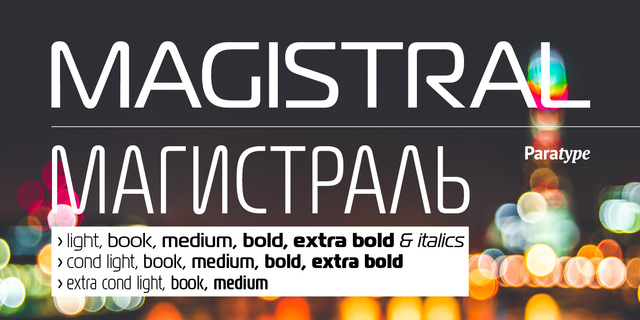
Первые три начертания гарнитуры были разработаны в фирме ПараТайп (ПараГраф) в 1997 году дизайнером Дмитрием Кирсановым на основе эскизов московского дизайнера-графика Андрея Деонисовича Крюкова (1923-1997). Первоначальный вариант рисунка был разработан Крюковым в конце 60-х годов как фирменный шрифт для использования на железнодорожном транспорте. В пропорциях и в элементах конструкции шрифта заметно влияние шрифта Евростайл (Eurostile, 1962) Альдо Новарезе. Предназначен для применения в рекламе и акциденции. Гарнитура откорректирована и дополнена новыми начертаниями тем же автором в 2009 году.
Ассоциации c начертанием Magistral Extra Cond MediumКачества и характер:
точный, ровный, убедительный, прямоугольный, стабильный, твердый, серьезный, надежный, уверенный, сильный, устойчивый, индустриальный, техногенный, космический, лаконичный, крутой, футуристичный, амбициозный, городской, урбанистичный, урбанистический, инженерный, чертежный, спортивный
техника, прибор, промышленность, станок, инструмент, электростанция, энергетика, завод, тренажеры, фантастика, инновации, архитектура, наука, гаджет, девайс, дизайн, блокбастер, боевик, экшен, игра, Айтишник, IT, айтишник, айти, технологии, город, урбанистика, транспорт, автомобиль, инженер, космос, киберспорт, спорт Стилистика: